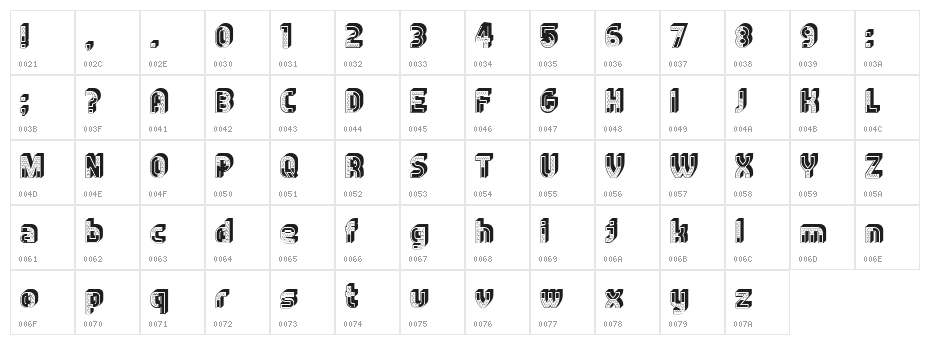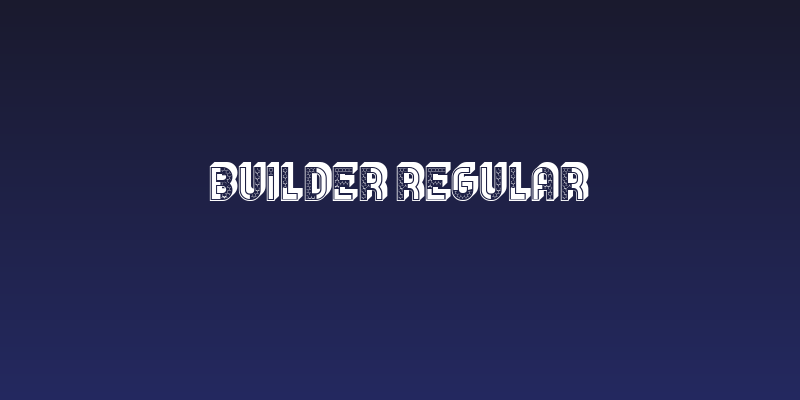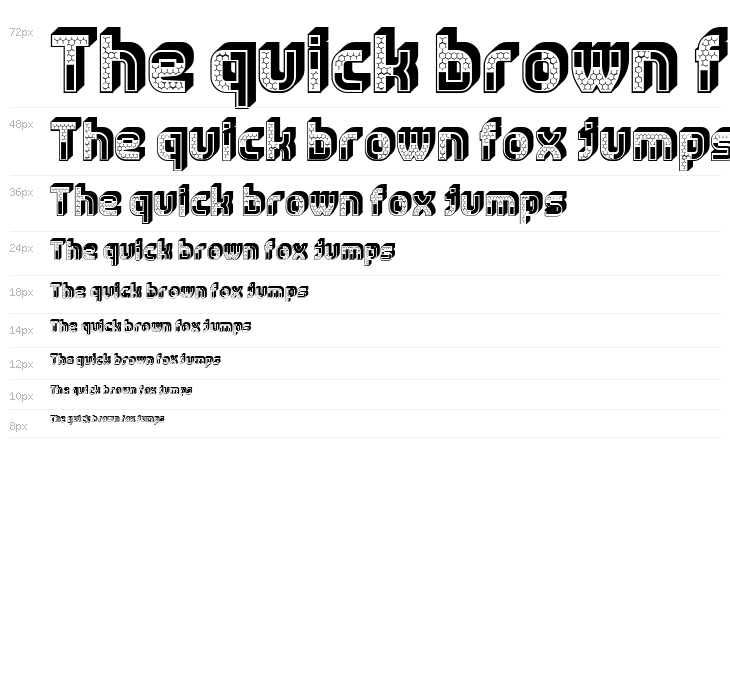
Builder Regular Font
Fonts by Vladimir Nikolic
| Gesamtstil | Modern, Decorative |
| Vorgeschlagene Projekte | Ideal for branding, posters, and headlines where a bold, modern look is desired. |